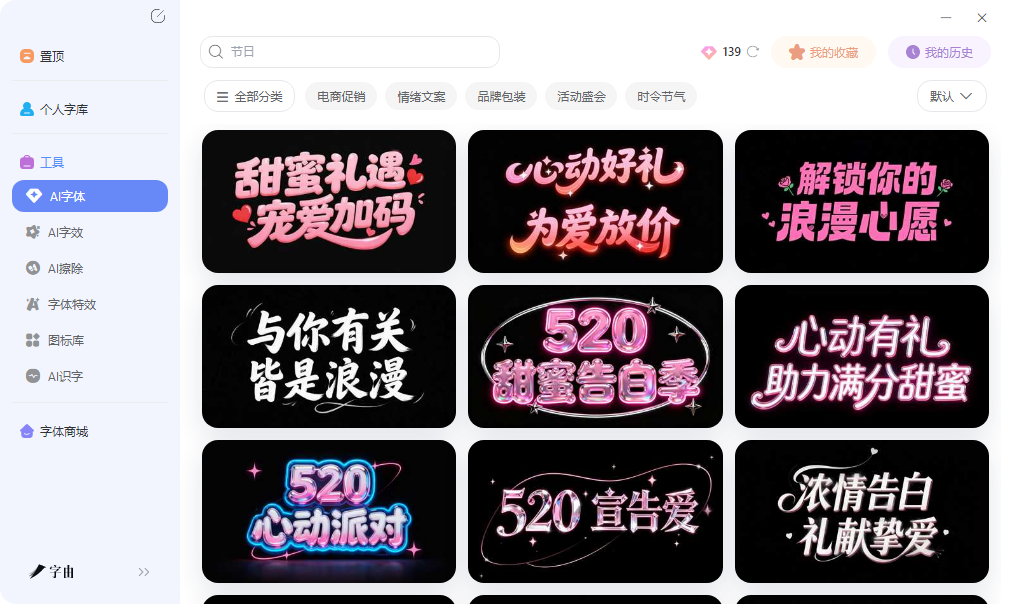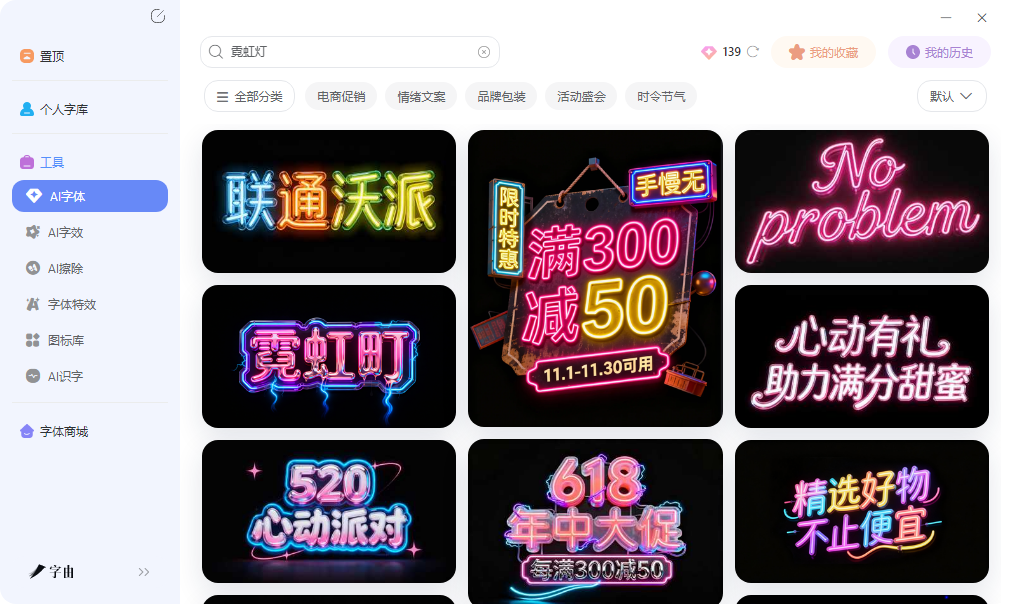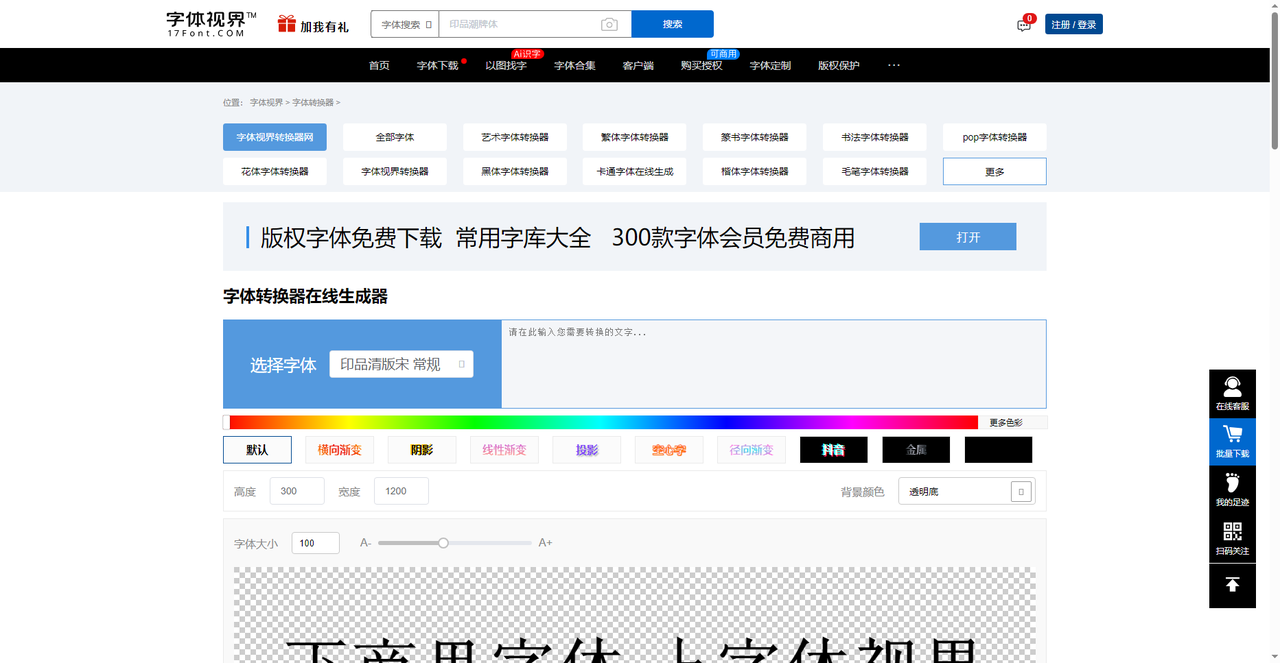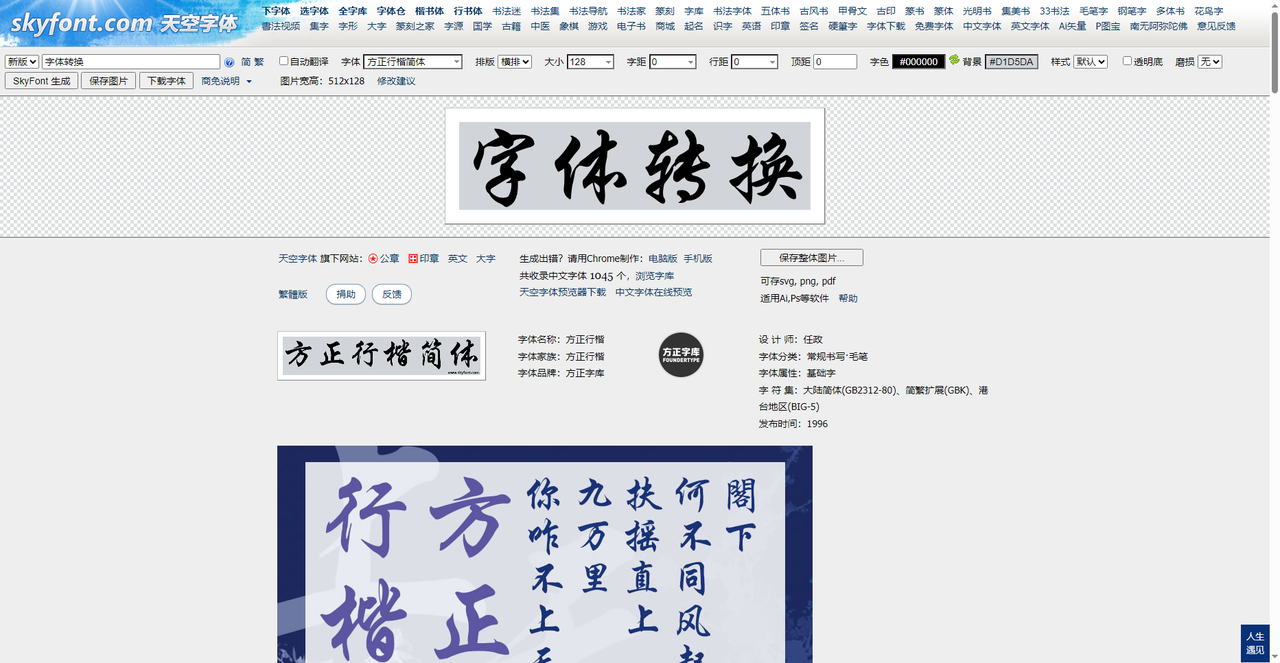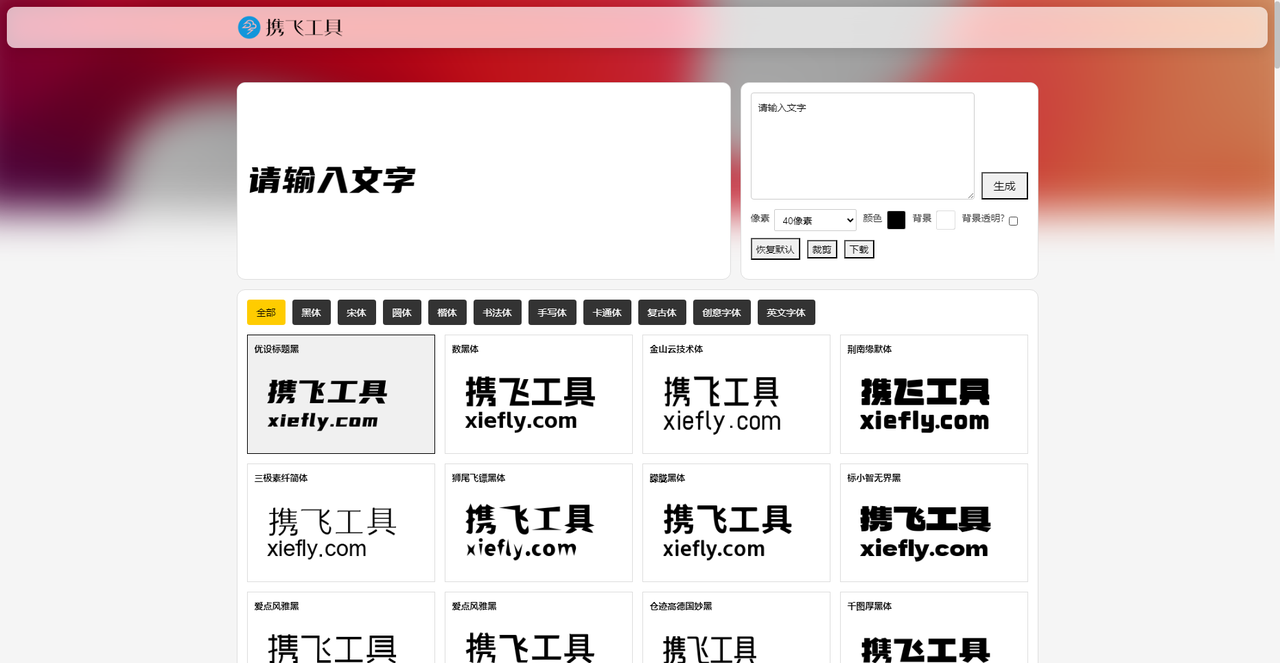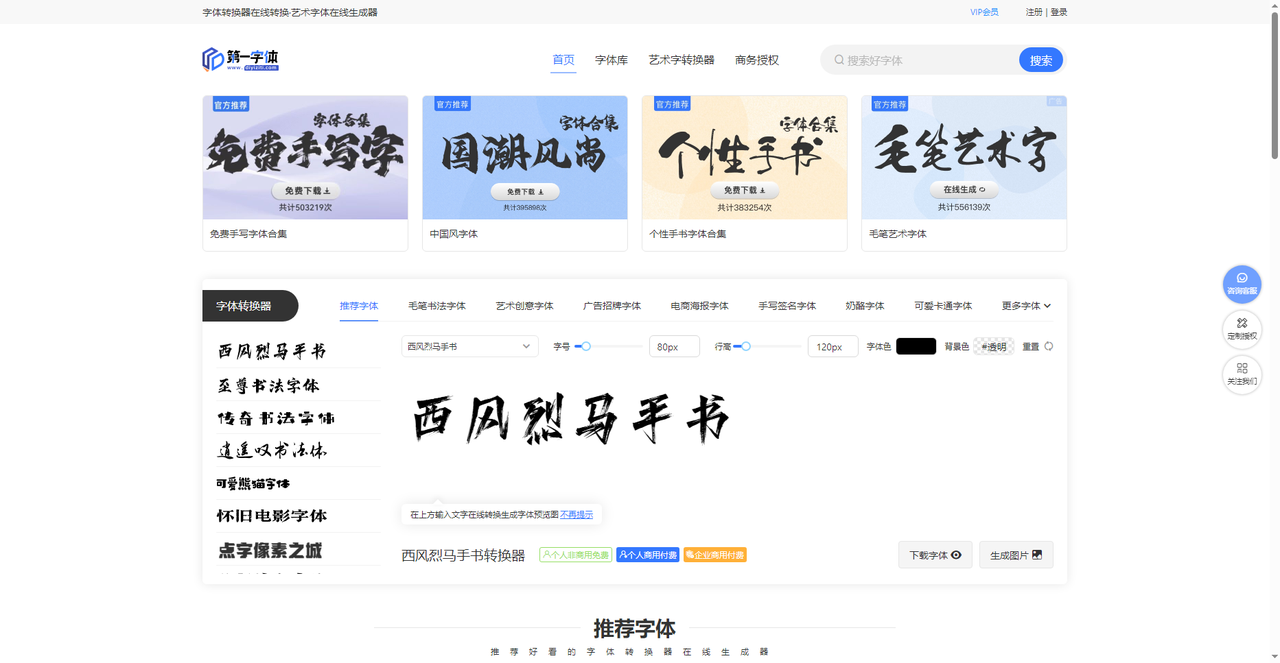
在线字体生成器,一键转换花体、哥特、霓虹字
做海报封面、社交媒体配图,标题字总是觉得不合适。系统自带的字体太普通,想做个霓虹灯效果,在PS里调外发光、内阴影、混合模式,参数一多就手忙脚乱。其实现在有不少在线字体生成器,输入文字,选个特效模板,几秒钟就能出一张带效果的艺术字图。不用学设计,不用装软件。今天挑了5款实测好用的工具,有专业级AI模板,有各种特效调节,还有海量中文字体库。输入文字,选个顺眼的风格,几秒钟就能让普通字变得与众不同。
其实设计师最贵的不是软件也不是什么设备,而是时间。做一个海报标题,最耗时的环节往往是去一个一个试字体和特效,一个参数一个参数地调。字由的AI字体模块则是完美地解决了这个问题,你不需要从零开始,只需要在现成的方案里做减法——去掉不合适的,留下你喜欢的就可以了。
字由AI字体的标签栏按设计方向分类,包括国潮、霓虹灯、金属质感、手写书法、电商促销等。用户根据项目类型选择一个标签,系统会筛选出对应的模板列表。每款模板已经预置了字体、特效、排版和背景参数。用户输入自己的文案后,点击生成按钮,约10到15秒可以得到一张透明背景的艺术字图片。生成后可下载PNG格式,直接用于海报、封面或Banner。
并且字由每天登录赠送免费算力,日常使用不需要付费。这个过程不需要用户手动调整字体大小、发光颜色或阴影参数,所有效果都是模板自带的。如果对生成结果不满意,可以换一个模板重新生成,或微调文案字数保持与模板示例接近。字由AI字体适合快速产出标题图的场景,比如电商促销主图、自媒体封面、活动海报标题等。
第二个网站是字体视界旗下的“字体转换器在线生成器”。它的功能非常丰富,不只是简单的文字转换,而是提供了专业的特效调节面板。在页面中输入文字后,可以选择字体,然后调节多种特效:更多色彩、默认、横向渐变、阴影、线性渐变、投影、空心字、径向渐变、抖音风格、金属质感等。还可以设置高度、宽度(默认1200x300),背景颜色支持透明底,字体大小可调。设置完成后,点击“下载图片”即可获得高清艺术字图。页面还提供了“批量下载”功能,适合需要一次性生成多张图的用户。
这个站的特效非常多样,尤其是“抖音风格”和“金属质感”,适合做短视频封面和电商主图。如果你想要一个带渐变阴影或者空心描边的标题字,不用在PS里慢慢调,在这里点几下就能搞定。而且它支持透明背景,方便直接叠加到其他设计上。
第三个网站是天空字体。它提供了一个“新版字体转换”工具,专门用于中文字体的在线预览和转换。页面中可以输入文字,选择字体(如“方正行楷简体”),设置排版方向(横排),调整字号(最大128)、字框、行距、顶距。还可以自定义字体颜色、背景颜色,生成后可以保存为图片,也支持下载字体文件。天空字体的特色在于它收录了1045个中文字体,并且每款字体都有详细介绍。例如“方正行楷”由设计师任政创作,属于毛笔书写体,字符集支持GB2312-80、GBK、BIG-5。页面中还展示了“你九扶何阁”等预览示例。如果你需要一款正版的中文行楷或书法字体,又想在下载前看到实际排版效果,天空字体的在线预览功能很实用。生成后的图片可以用于参考,但商用需购买授权。
第四个网站是携飞工具。它是一个在线字体转换器,提供了非常庞大的中文字体库。页面中可以看到字体分类:黑体、宋体、圆体、楷体、书法体、手写体等。每个分类下都有大量具体字体。
操作很简单:输入文字,选择字体,设置像素大小、颜色,可以选择背景透明,点击“生成”即可预览效果。然后可以裁剪下载图片。这个站的优势是字体数量多、分类清晰,而且很多字体是免费可商用的(如“千图厚黑体”)。如果你需要快速预览某款字体在自己的文案下的效果,或者批量比较不同字体,携飞工具比挨个下载安装快得多。
第五个网站是第一字体网。它的“字体转换器”板块提供了多种书法艺术字体转换,首页推荐了“西风烈马手书”“传奇书法字铺”“逍遥双书法体”“可爱熊猫字体”“怀旧电影字体”等。用户输入文字后,可以选择字体(如“西风烈马手书”),调整字号(80px)、行高(120px)、字体色、背景色(支持透明),然后点击“生成图片”即可预览。转换结果分为“个人非商用免费”“个人商用付费”“企业商用付费”三种授权方式,用户可以根据需求选择。
第一字体网的特色是书法字体资源丰富,尤其适合做国潮风、中式招牌、古风海报的标题字。例如“西风烈马手书”笔触苍劲有力,有强烈的书法质感。如果你需要一款有文化底蕴的书法艺术字,又不想自己写,这个站可以直接生成图片。商用的话记得购买授权,避免侵权。
基本上你想要的字体转换效果都能在这篇文章中找到,其中字由最适合不想纠结风格、追求效率的用户,用“风格标签”快速锁定方向;字体视界特效丰富,阴影、渐变、空心、抖音、金属一应俱全,适合精细调节;天空字体专注中文字体在线预览,方正行楷等书法字体排版效果一目了然;携飞工具字体库庞大,分类清晰,适合快速对比不同字体;第一字体网专攻书法艺术字,西风烈马手书等风格一键生成,商用授权明确。输入你的文案,选一个顺眼的工具,几秒钟就能拿到一张能用的艺术字图。不用学PS,不用调参数,在线就能搞定。